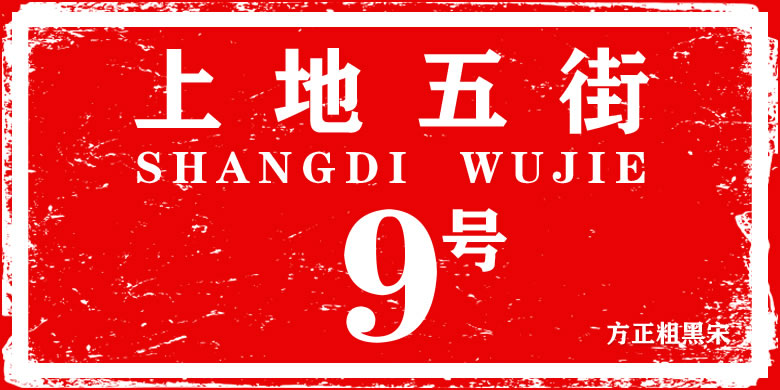
方正粗黑宋简体
方正粗黑宋简体是一款非常漂亮的艺术字体,方正粗黑宋简体广泛用于各种书刊、画册、包装、字体设计的设计中,方正粗黑宋简体是TrueType字体,方正粗黑宋简体也是报纸和杂志和书籍中常用的字体, 设计师常用字体,主要用于海报、个性促进品牌标志设计、字体设计、等环境。
方正粗黑宋结合了黑体与宋体的特征,既有黑体粗壮的几何笔形,又有宋体起笔、折笔、收笔处的饰角,将黑体的庄严和宋体的灵动融为一体,赋予宋体一种中正、硬朗的特质。这款字体的笔画较粗,横画与竖画粗细接近。适用于正文标题和广告标语。